作为显示在屏幕、银幕上的字幕,一定要字体规整,不要使用美术体、草体等,而要方正得体,让人一目了然。字号的选择,首先不能过小,要让人很容易地辨认,看得清楚,然后还不能过大,要与整个屏幕图像成合适的比例、协调美观。颜色要朴素,不刺眼,还要与整个片子大多数时间里的背景要一定的对比度,也是让人能够看得清楚。
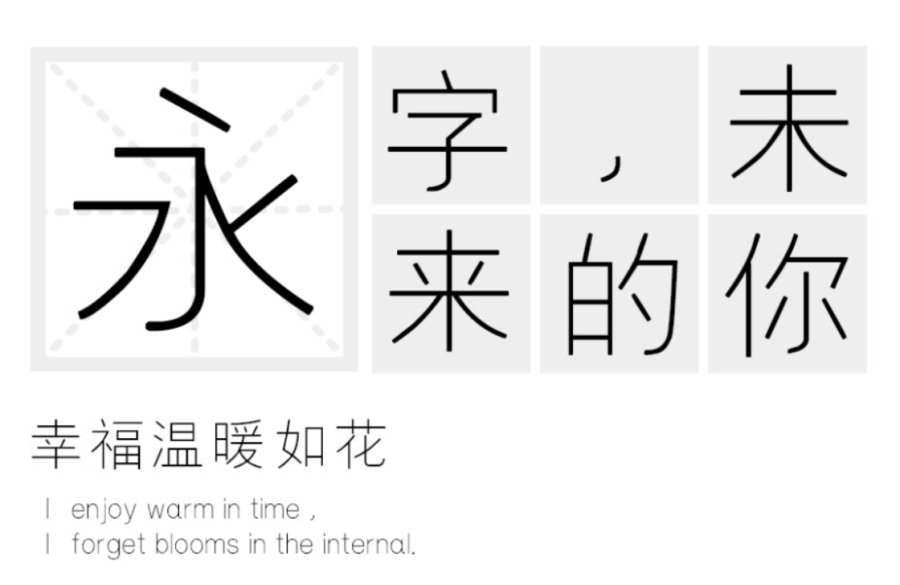
黑体作为现代设计的标志,粗细均匀、没有多余的修饰,给人的感觉十分干净,无疑是所有字体里呼声最高的。关于黑体的选择只存在一个问题,那就是:你究竟更喜欢哪一款黑体?先要给大家介绍的一款是“汉标细黑体”。这款细黑字形正方,笔形简练,风格简静优雅;追求远距离读取功能,笔画清晰、易于识别字体。
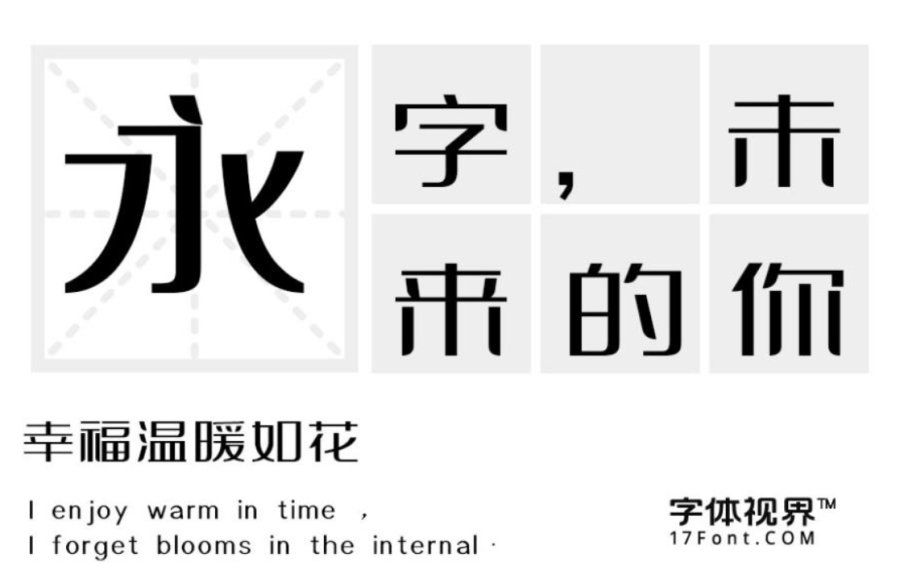
这款字体也是一款黑体字,“上首秀黑体”,整体特征方正稳重,笔画方中带圆。字体右下角转角处作圆角处理,整体结构刚中带柔,干净洒脱,同时洋溢着成熟、稳重、又不缺泛严谨的风格。
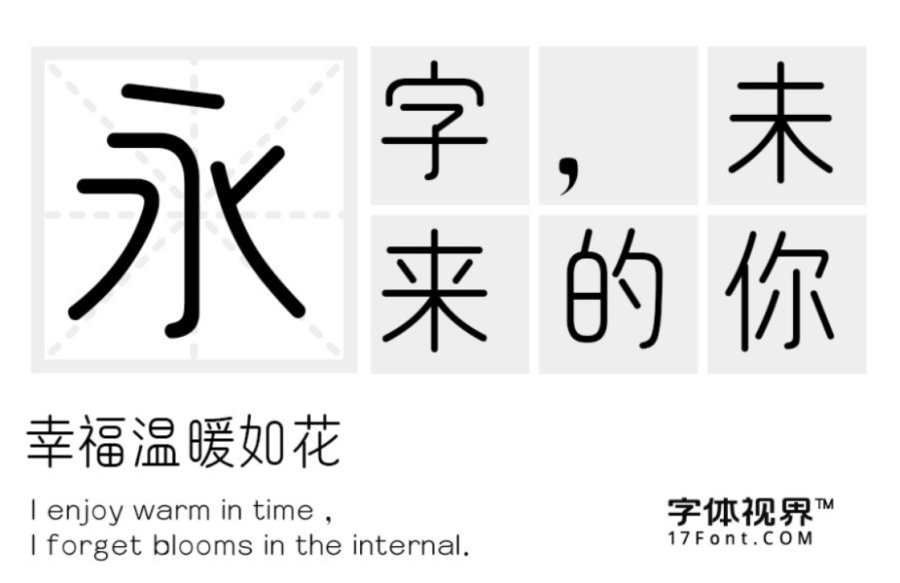
圆体作为黑体的变体,既清晰易读又简单明了。大投影放出来,配上小字号的圆体,用过你自然懂。三极古圆简体作品整体风格独特,具有古法圆通、朴拙之感,字形融合了象形、篆书等古朴字形,使其风格简洁明快,独具一格。字体轻巧简洁,古拙而不凡。粗细匀称,起笔收笔为圆头,折、钩、撇捺转折圆润饱满,具有古拙婉转的气质。视觉效果简洁易识别,实用性强。